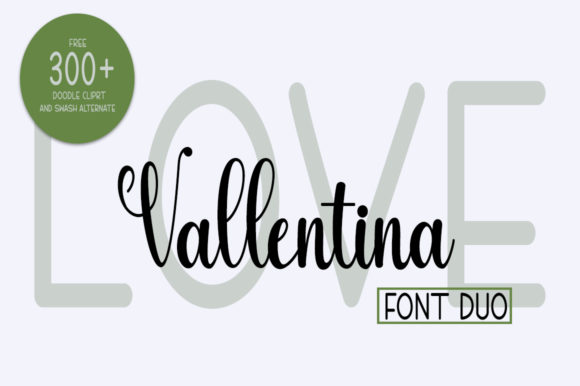
Love Vallentina Duo
Love Vallentina Duo – Análise Completa da Fonte Duo Mais Versátil de 2024
Se você está em busca de uma tipografia que una elegância e personalidade, Love Vallentina Duo chega como a solução perfeita. Esta fonte espetacular combina script e handwritten em um único pacote, trazendo caracteres que dançam ao longo da linha de base e dão vida instantânea a qualquer projeto.
- Dupla de estilos integrados: inclui a variante script fluida e a handwritten mais descontraída, permitindo alternar entre formal e casual sem perder consistência.
- Versatilidade extrema: ideal para convites de casamento, branding de moda, embalagens artesanais, posts de mídia social e até interfaces digitais.
- Legibilidade aprimorada: apesar do visual artístico, as letras mantêm clareza em tamanhos pequenos, facilitando seu uso em textos curtos e headlines.
Por que escolher Love Vallentina Duo?
Ao integrar Love Vallentina Duo ao seu fluxo criativo, você eleva o nível de qualquer projeto, graças ao seu design que “faz os caracteres dançarem”. A combinação de script sofisticado com a escrita à mão gera um efeito visual que captura a atenção do público e transmite autenticidade.
Casos de Uso Recomendados
- Cartões de visita e convites elegantes
- Logotipos de marcas de moda e beleza
- Campanhas de marketing digital e posts de Instagram
- Embalagens de produtos artesanais
- Websites de portfólio criativo
Conclusão – Vale a pena?
Sim! Love Vallentina Duo é mais que uma fonte; é uma ferramenta de storytelling visual que transforma ideias simples em experiências memoráveis. Se o seu objetivo é destacar-se no mercado com design de alto nível, não perca tempo: adicione Love Vallentina Duo ao seu arsenal criativo agora mesmo e veja seus projetos ganharem vida.